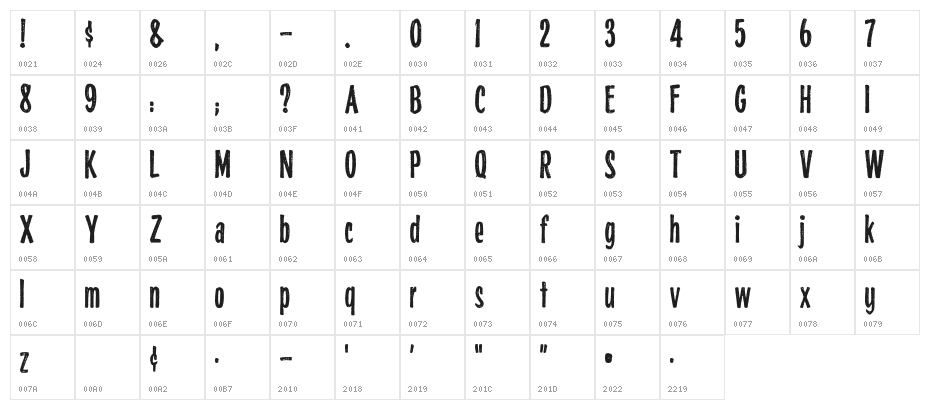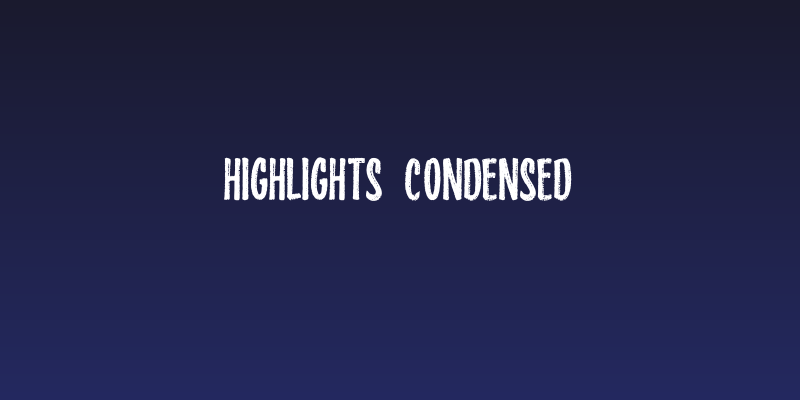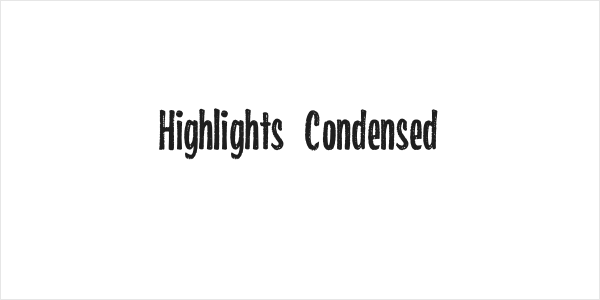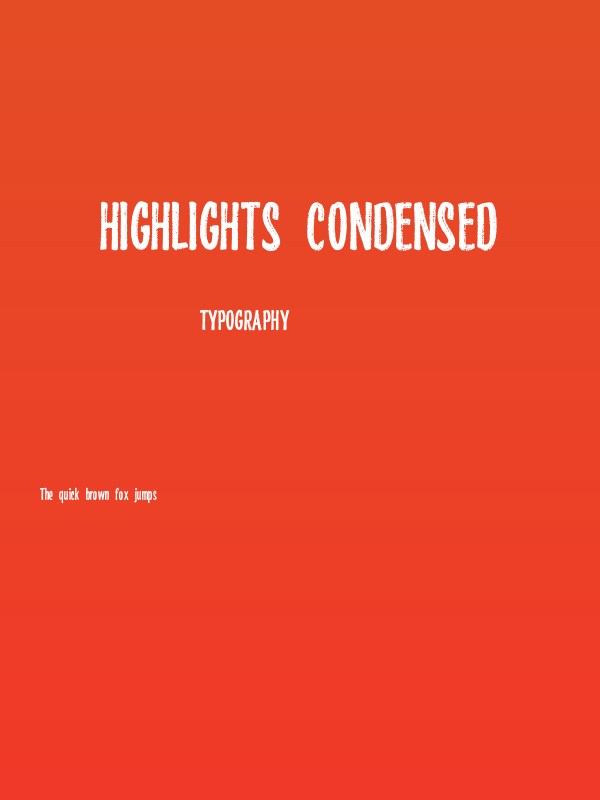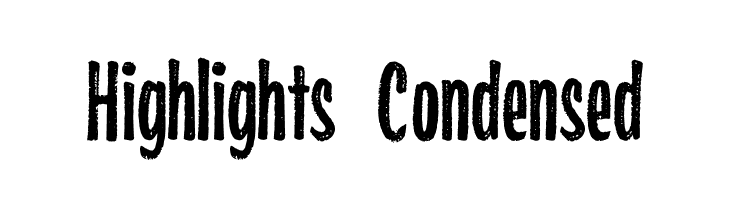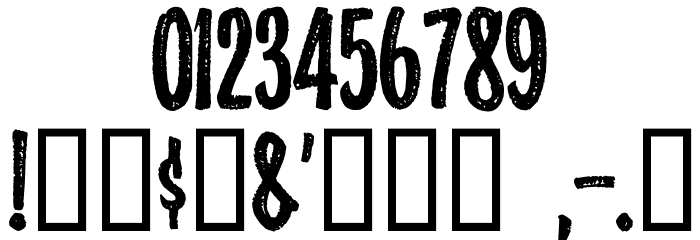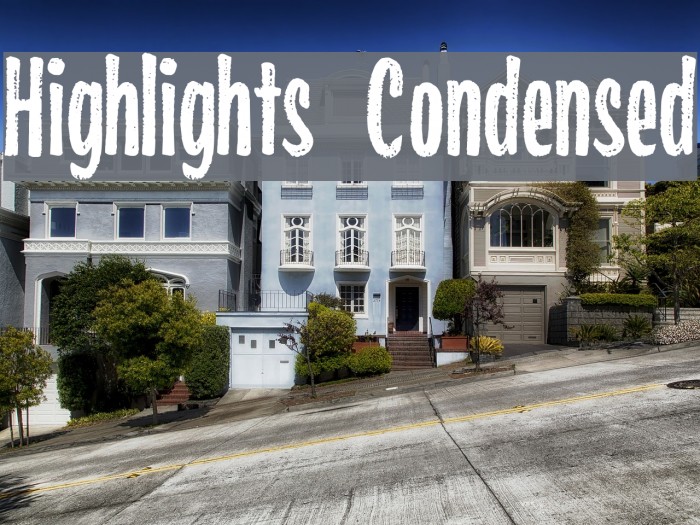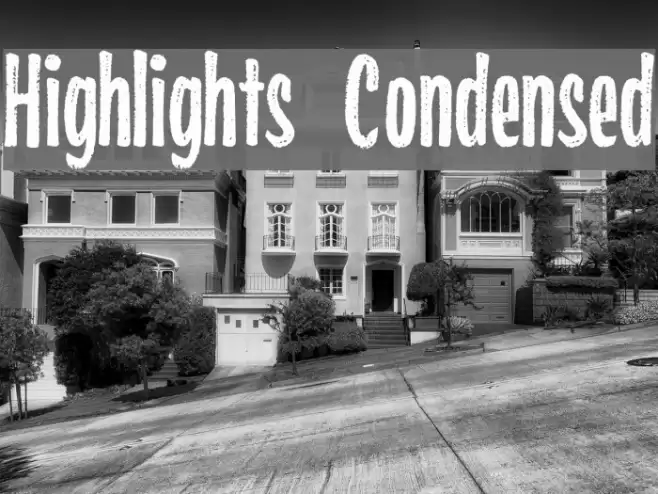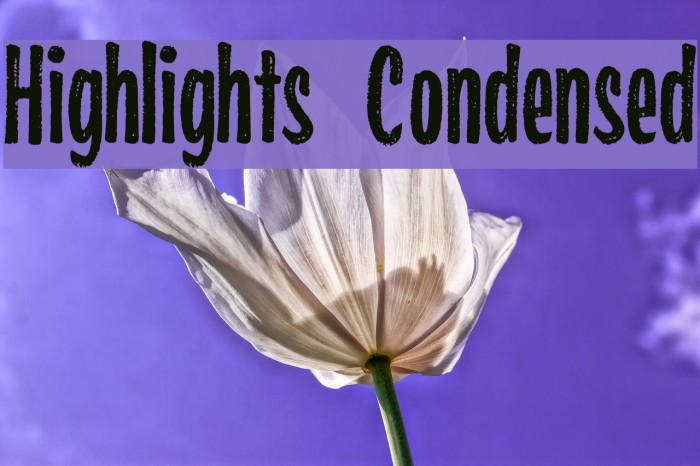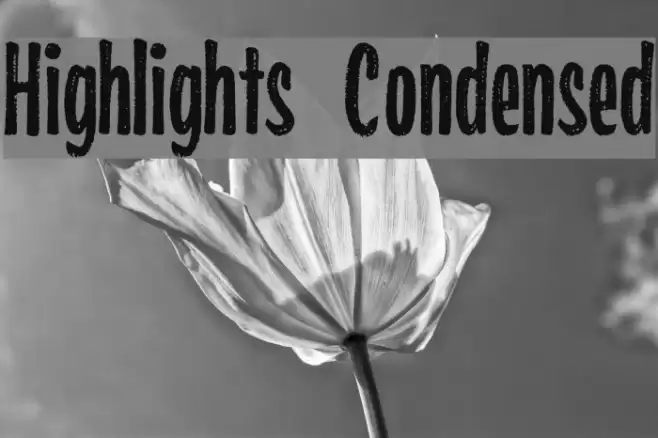
Highlights Condensed Font
✎ Messy
| Projetos propostos | Ideal for vintage-themed posters, logos, and branding materials where a bold and rugged look is desired. |